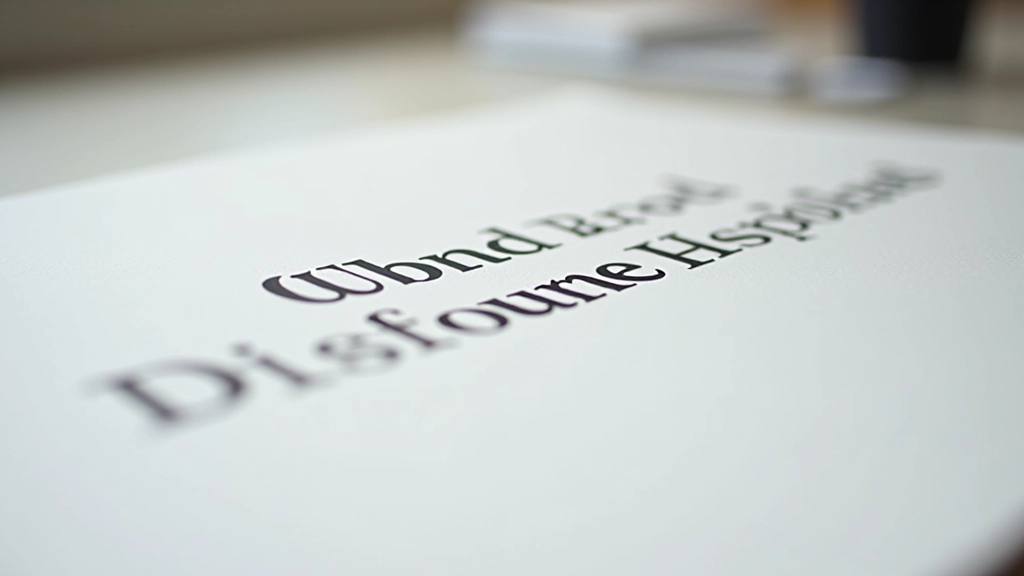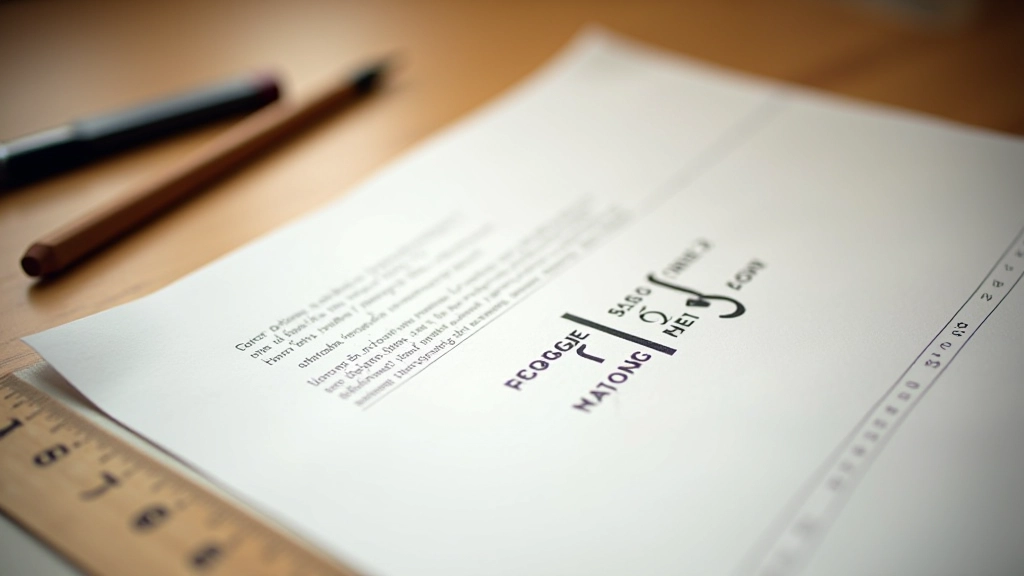
Buchstabenabstand perfektionieren
Wie man Kerning und Letter-Spacing richtig einsetzt, um Überschriften prägnanter und lesbar zu machen
Zum GuideWie du Buchstabenabstand, Wortabstand und Zeilenlängen optimierst — damit deine Texte nicht nur schön aussehen, sondern auch wirklich gelesen werden.
Details, die den Unterschied machen — und warum sie nicht ignoriert werden sollten.
Viele Designer denken, dass Typografie erst bei der Schriftwahl beginnt. Aber die echte Arbeit passiert danach — wenn du Leerzeichen, Abstände und Längenverhältnisse anpasst. Es’s die Mikrotypografie, die eine Website von durchschnittlich zu unvergesslich macht.
Mehr erfahrenRichtige Abstände = schnelleres Lesen
Optische Ausrichtung statt mathematisch
Gleiche Regeln auf allen Geräten
Auch für Dyslexiker und bei schlechtem Licht
Das ist’s nicht einfach ein Blog über Typografie. Es’s ein praktischer Leitfaden für echte Probleme, mit denen echte Designer kämpfen. Jeder Guide ist aus echten Projekten entstanden, nicht aus Theorie.
Kerning ist die Anpassung des Abstands zwischen einzelnen Buchstaben-Paaren, um visuell ausgewogen auszusehen. Letter-Spacing ist eine gleichmäßige Erhöhung des Abstands zwischen allen Buchstaben. Kerning ist subtil und optisch, Letter-Spacing ist mathematisch und einheitlich.
Die Faustregel liegt zwischen 45 und 75 Zeichen pro Zeile. Bei längeren Zeilen verlieren Leser die Orientierung. Bei kürzeren Zeilen wird das Auge zu oft unterbrochen. Auf mobilen Geräten sollte es näher an 40-50 Zeichen sein.
Absolut. Studien zeigen, dass richtige Abstände und Zeilenlängen die Lesgeschwindigkeit um bis zu 20% erhöhen und die Lesbarkeit deutlich verbessern. Es’s nicht sichtbar, aber es’s definitiv spürbar.
Nein. CSS bietet alle Tools, die du brauchst: letter-spacing, word-spacing, line-height, und text-align: justify. Du kannst gute Mikrotypografie direkt in deinen Webdesign-Workflow integrieren.